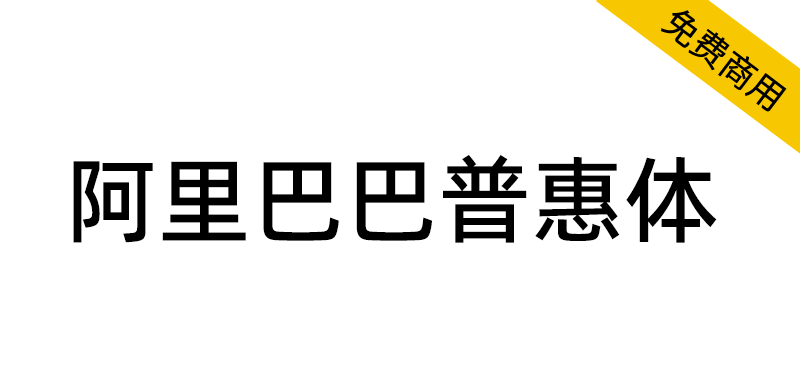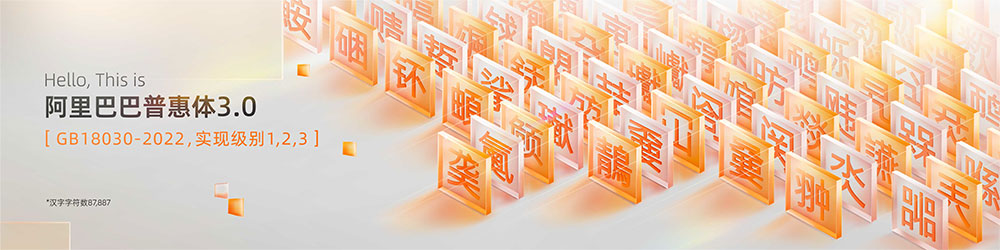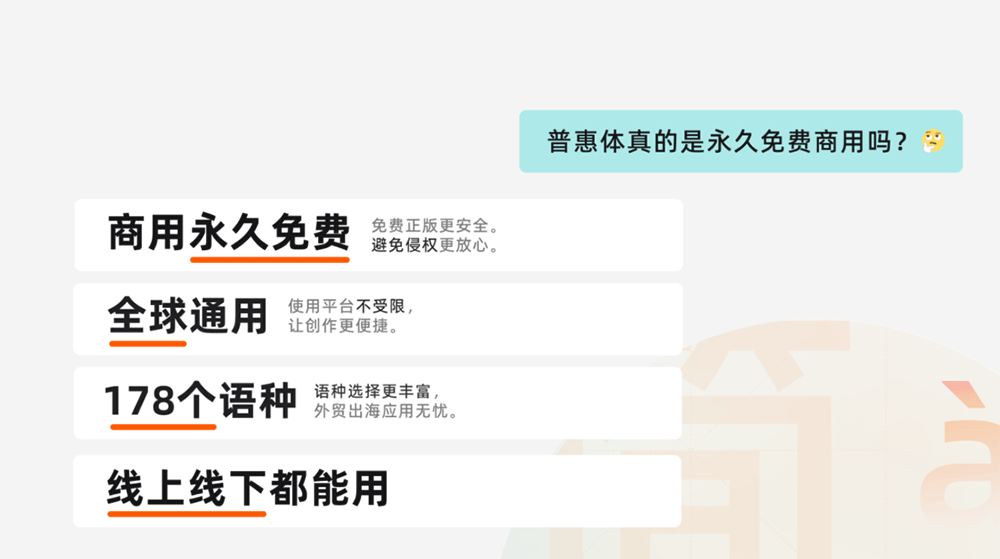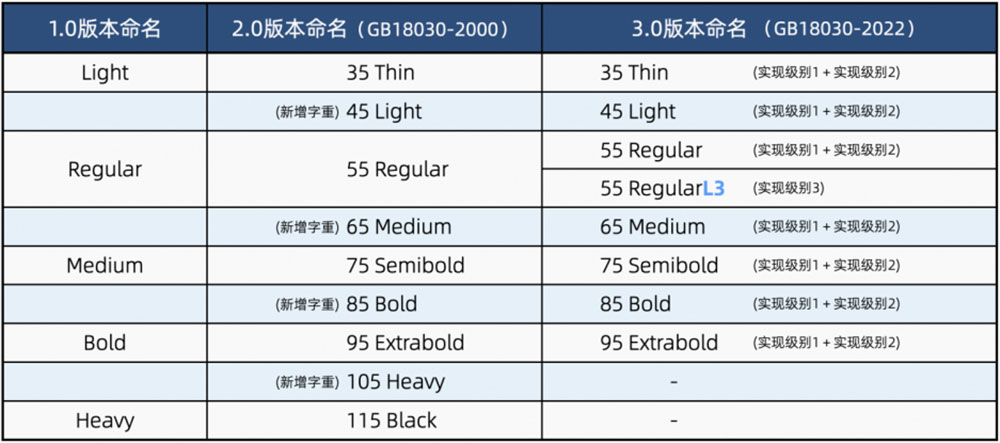
阿里巴巴普惠体是一套全球永久免费正版商用的字体家族,目前涵盖178个语种。阿里巴巴普惠体是一款由中国企业首次发布的可面向全场景使用的免费商用正文字体。以「普惠」之名诞生,阿里巴巴普惠体开放商业授权给所有个人和商家,让更多用户可以免费使用这款字体,以普惠设计助力商业生态增长。
阿里巴巴普惠体3.0为一套符合新国家标准GB18030-2022的简体中文字符集,包含GB18030-2022强制规范三个实现级别:实现级别1+实现级别2标准规格的7字重、实现级别3标准规格的Regular 单一字重。7字重共194,460个全形汉字。包含拉丁字母、希腊字母、西里尔字母、标点符号。
* GB18030-2022 是新版的汉字编码字符集国家标准,是全文强制性标准,市场上销售的产品必须符合。详见:全国标准信息公共服务平台(https://std.samr.gov.cn/search/std?q=GB18030-2022)
【GB18030-2022 实现级别摘要】GB18030-2022标准执行方式改为三个实现级别,不再分为强制部分和推荐部分。
1. 实现级别1:用于最基本的中文信息处理和交换
实现级别1在GB18030-2022的标准中,要求在GB18030-2005强制部分的基础上去掉新标准中删除的编码部分,并加上在CJK基本平面下的新增的66个汉字共27,584汉字。任何适用的产品均应满足实现级别1的要求。
2. 实现级别2:用于促进《通用规范汉字表》的信息化应用
实现级别2包含实现级别1。此外,实现级别2还支持《通用规范汉字表》中的没有包含在实现级别1之内的编码汉字196汉字。系统软件及支撑软件,应满足实现级别2的要求。
3. 实现级别3:用于解决信息系统生僻字问题
实现级别3包含实现级别2。此外,实现级别3 还支持本文件规定的全部汉字及康熙部首部分。
用于政务服务和公共服务的产品应满足实现级别3的要求。
什么是GB18030-2022版本?阿里巴巴普惠体3.0(GB18030-2022版本)对比普惠体2.0有哪些不一样?
1.、新规定分三个实现级别,按级别「强制性标准」:符合相应实现级别的系统软件产品,应提供相应实现级别范围内全部字符的输入输出功能。
a. 实现级别2(系统软件及支撑软件为必要项)。实现级别2:系统软件及支撑软件,应至少满足实现级别2的要求。系统软件及支撑软件包括但不限于操作系统、数据库管理系统、中间件(软件产品分类按照GB/T 36475中的规定)。
b. 实现级别3(用于政务服务和公共服务的产品则为必要项)。实现级别3:政务服务和公共服务行业包括但不限于铁路运输业、道路运输业、水上运输业、航空运输业、多式联运和运输代理业、邮政业、货币金融服务、保险业、土地管理业、卫生、国家机构、社会保障等(行业分类按照GB/T 4754中的规定)。
2.、新规的主管为 国家市场监督管理总局 国家标准化管理委员会
GB18030-2022版本
● 汉字总数:87,887个汉字,全覆盖《通用规范汉字表》
● 标准性质:全文强制
● 实现级别要求:规定三级实现要求:
○ 实现级别1:27,584个汉字。
○ 实现级别2:实现级别1+196个汉字覆盖《通用规范汉字表》。
○ 实现级别3:全部87,887个汉字。